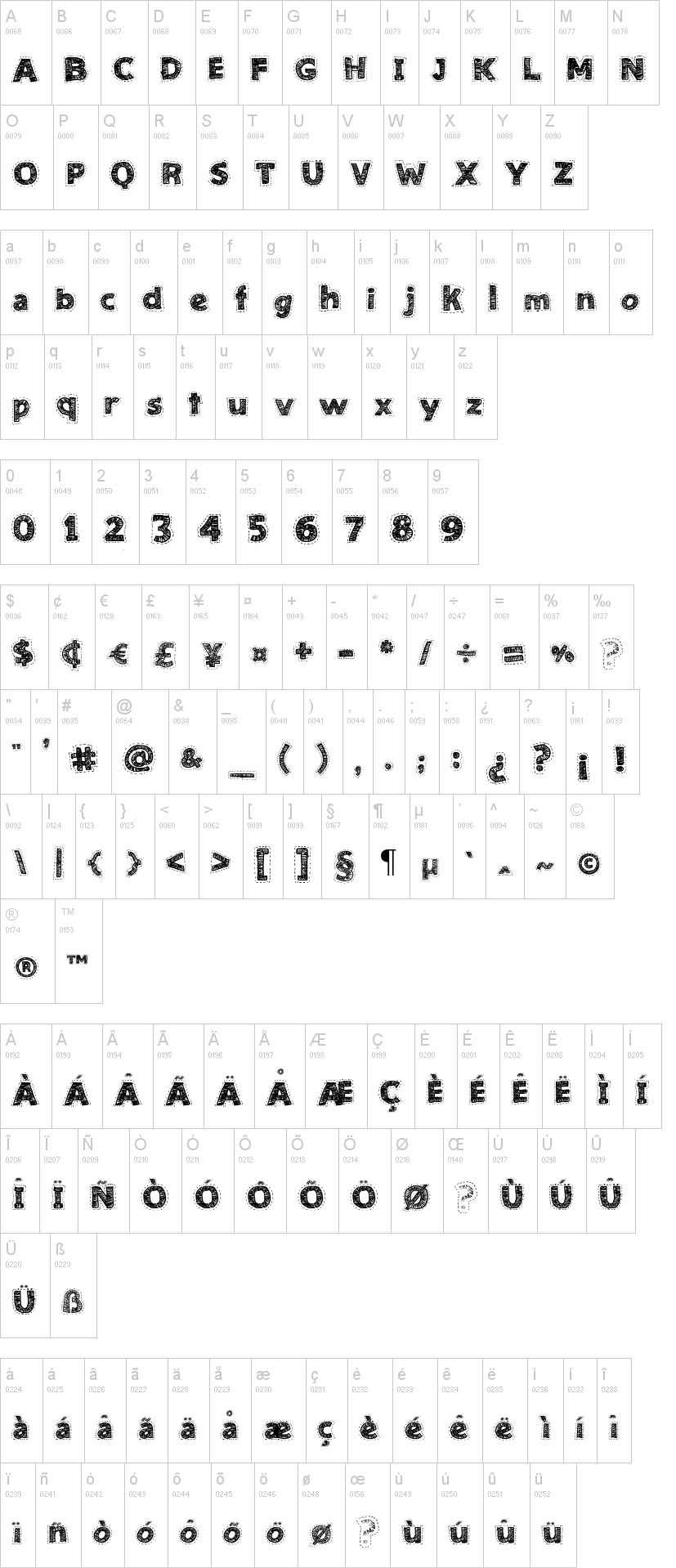
Needlework Good 是一种手写风格的字体,具有优美、流畅和自然的特点。该字体适用于各种手工制作、纺织、刺绣、织布、针织、编织等艺术和手工艺项目的设计。它的笔画线条流畅,具有传统针织、刺绣和风格的味道。该字体还有一些变化和装饰,如粗细不均的线条、手写效果、一些装饰图案和手绘效果等等。整体来说,Needlework Good 是一种非常适合手工艺爱好者、设计师和艺术家使用的字体。内容介绍
Needlework Good是一款非常不错的手写艺术字体,具有很好的视觉感,适合于文化类的宣传设计、商业类品牌的广告和产品包装设计以及个性化文字排版等较多场景。